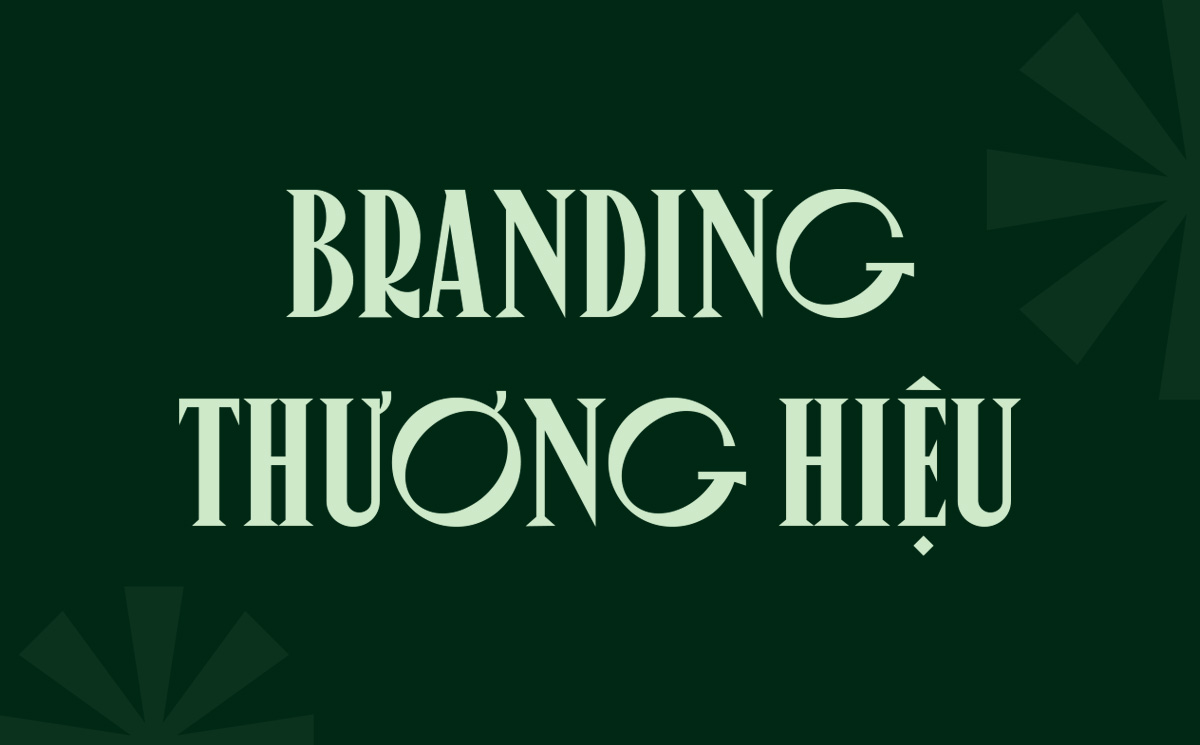
Font SVN Canopee Việt hóa – Font chữ hiện đại serif có chân
Font SVN Canopee Việt hóa là sự kết hợp hoàn hảo giữa nét đẹp cổ điển thanh lịch và tinh thần hiện đại phá cách, mang đến giải pháp typographic đột phá cho mọi nhà thiết kế. Được tinh chỉnh tỉ mỉ với bộ dấu tiếng Việt chuẩn xác, font chữ hiện đại serif có chân này sẽ giúp các sản phẩm sáng tạo của bạn trở nên ấn tượng, sang trọng và thu hút người xem ngay từ cái nhìn đầu tiên. Nếu bạn đang tìm kiếm một typography vừa độc đáo vừa giữ được sự chuyên nghiệp cho dự án nhận diện thương hiệu hay ấn phẩm truyền thông, SVN Canopee chính là sự lựa chọn không thể bỏ qua.
Font SVN Canopee Việt Hóa – Font Chữ Hiện Đại Serif Có Chân Đỉnh Cao Cho Thiết Kế Đồ Họa
Trong thế giới thiết kế đồ họa đương đại, việc lựa chọn font chữ đóng vai trò quyết định đến 80% cảm xúc và thông điệp mà thương hiệu muốn truyền tải. Font SVN Canopee Việt hóa nổi lên như một hiện tượng trong cộng đồng designer nhờ sự hòa quyện độc đáo giữa cấu trúc serif cổ điển và tư duy thiết kế hiện đại. Bộ font này không chỉ giải quyết triệt để bài toán thẩm mỹ mà còn mang lại sự linh hoạt tối đa cho nhiều loại hình ấn phẩm thiết kế khác nhau.
1. Thiết Kế Serif Hiện Đại Mang Hơi Thở Vintage Độc Đáo
Font SVN Canopee gây ấn tượng mạnh mẽ nhờ sự hòa trộn tinh tế giữa phong cách Art Deco thập niên 1920 và xu hướng typographic đương đại. Sự kết hợp giữa các đường nét uốn lượn mềm mại cùng hệ thống chân chữ (serif) sắc sảo tạo nên vẻ đẹp sang trọng, quý phái nhưng không kém phần trẻ trung. Nhờ cấu trúc phân bổ trọng lượng chữ độc đáo với sự tương phản rõ rệt giữa nét thanh và nét đậm, bộ font chữ hiện đại serif có chân này mang lại chiều sâu thị giác đặc biệt, giúp các tiêu đề chính nổi bật hoàn toàn trên mọi nền thiết kế.</p>
2. Tối Ưu Hóa Tiếng Việt Hoàn Hảo Cho Nhà Thiết Kế Việt
Phiên bản SVN Canopee Việt hóa được tinh chỉnh cẩn trọng từng đường nét ký tự và hệ thống dấu tiếng Việt (ngã, hỏi, sắc, huyền, nặng, các dấu phụ ơ, ư, ă, ê…). Khác với nhiều font chữ ngoại nhập bị lỗi font hoặc lệch vị trí dấu khi gõ tiếng Việt, SVN Canopee giữ nguyên được khoảng cách kerning hoàn hảo và thẩm mỹ tổng thể của bản gốc. Điều này giúp các nhà thiết kế tại Việt Nam dễ dàng sáng tạo các nội dung truyền thông bằng tiếng Việt mà không gặp bất kỳ trở ngại nào về mặt hiển thị.</p>
3. Ứng Dụng Đa Dạng Trong Thiết Kế Thương Hiệu Và Nhận Diện
Nhờ vẻ đẹp vượt thời gian, font SVN Canopee Việt hóa phù hợp với vô số lĩnh vực thiết kế khác nhau. Từ ngành thời trang cao cấp, mỹ phẩm, trang sức, kiến trúc cho đến nghệ thuật, truyền thông và ẩm thực, bộ font này đều hoàn thành xuất sắc vai trò truyền tải thông điệp thương hiệu.
Một số ứng dụng tiêu biểu của font chữ hiện đại serif có chân này bao gồm:
• Thiết kế Logo và Identity: Tạo điểm nhấn định vị thương hiệu cao cấp, thanh lịch và giàu tính nghệ thuật.
• Bìa Tạp Chí và Poster: Làm nổi bật các tiêu đề bài viết (Headlines), bìa sách, poster sự kiện triển lãm hoặc chương trình âm nhạc.
• Bao Bì Sản Phẩm: Nâng tầm giá trị thẩm mỹ cho bao bì nước hoa, rượu vang, hộp quà tặng và các dòng sản phẩm xa xỉ.
• Social Media & Banner Quảng Cáo: Giúp các bài đăng trên Facebook, Instagram, TikTok thu hút ánh nhìn nhờ phong cách hiển thị khác biệt.
4. Khả Năng Kết Hợp Typography Linh Hoạt Và Sáng Tạo
Một trong những ưu điểm vượt trội của SVN Canopee là khả năng phối hợp tuyệt vời với các bộ font chữ khác. Khi đóng vai trò là font tiêu đề (Display Font), bạn có thể dễ dàng kết hợp SVN Canopee với các font Sans-serif tối giản (như Helvetica, Montserrat, Futura) cho phần văn bản nội dung (Body Text) để tạo ra sự tương phản thị giác hài hòa. Sự phân cấp thị giác rõ ràng này giúp người đọc dễ dàng tiếp nhận thông tin, đồng thời nâng cao tính chuyên nghiệp cho toàn bộ bản thiết kế.</p>
5. Tương Thích Mượt Mà Trên Mọi Phần Mềm Thiết Kế
Bí Quyết Phối Font Chuẩn Chuyên Nghiệp Với SVN Canopee
Để tận dụng tối đa vẻ đẹp của bộ font hiện đại serif có chân này, nhà thiết kế có thể áp dụng những nguyên tắc phối font hiệu quả sau đây:
1. Quy tắc tương phản: Sử dụng SVN Canopee cho các tiêu đề lớn (H1, H2) và kết hợp với một font Sans-serif mảnh, không chân ở phần thân bài để tạo độ thoáng cho mắt người đọc.
2. Quy tắc đồng điệu cổ điển: Phối hợp SVN Canopee với các font Serif mang phong cách Old Style cho các thiết kế mang tính hoài cổ, sang trọng như thiệp cưới cao cấp hoặc catalogue nghệ thuật.
3. Kiểm soát khoảng cách chữ (Tracking & Kerning): Khi dùng Canopee ở kích thước chữ lớn cho banner hoặc poster, việc mở rộng nhẹ khoảng cách giữa các chữ cái sẽ tạo nên cảm giác thoáng đãng, sang trọng và chuẩn nghệ thuật chỉnh chu.